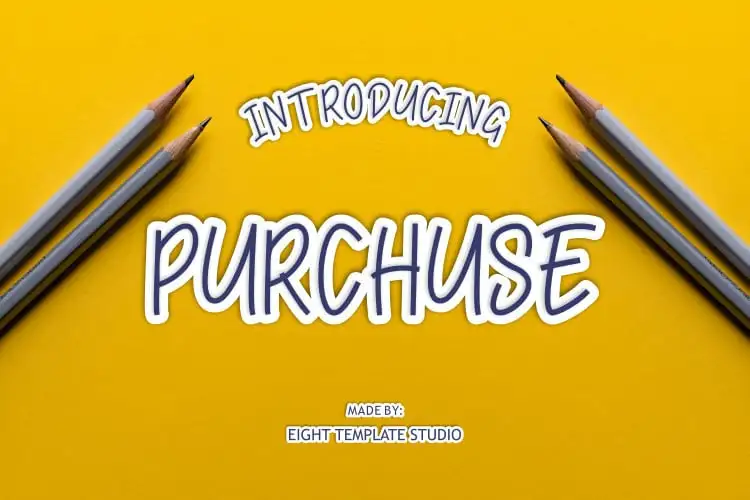
Purchuse Handwritten Font – Download Grátis
A fonte “Purchuse Handwritten Font” é uma escolha perfeita para designers que desejam adicionar um toque natural e aconchegante aos seus projetos. Suave e amigável, esta fonte escrita à mão possui um estilo único e natural que se adequa a uma ampla variedade de designs. O potencial da “Purchuse Handwritten Font” está limitado apenas pela criatividade do designer. Este é mais do que simplesmente uma ferramenta de impressão; ele é um artifício de design capaz de dar vida e personalidade a seus projetos, permitindo-lhe explorar a imaginação sem fim. Seja para criar cartões de aniversário, banners de marketing ou até mesmo elementos gráficos em aplicativos móveis – “Purchuse Handwritten Font” é uma fonte perfeita para transformar seus ideais em realidade.